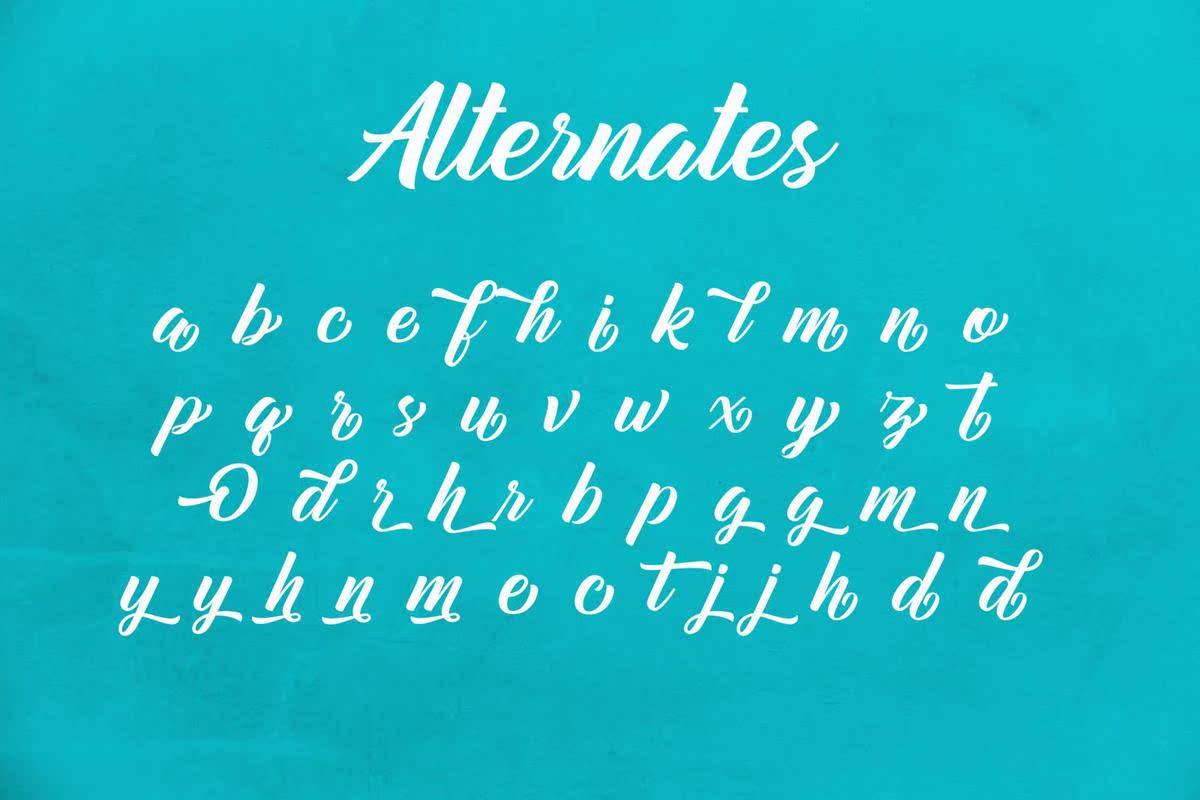
Mountainbridge是一种古老的脚本字体,精心制作,成为人们的最爱。它的偶然变化使它看起来非常贴近地球,可读性强,最终用途广泛。Mountainbridge无论是在繁忙的背景下还是在独立的标题下,在任何上下文中都会显得非常出色!这是一种编码方式,意味着你可以使用巨大的符号和SwasheSwithease!它还具有丰富的特殊功能,包括交替的PH值和连字。山桥是一种古老的脚本字体,经过精心制作,成为人们的最爱。它的偶然伤害使它看起来非常贴近地球,易于阅读,最终具有难以置信的多能性。山桥在任何上下文中都会显得杰出,无论是在忙碌的背景下还是在独立的标题下!这是一种编码方式,意味着你可以使用巨大的符号和SwasheSwithease!它还具有丰富的特殊功能,包括交替的PH值和韧带。